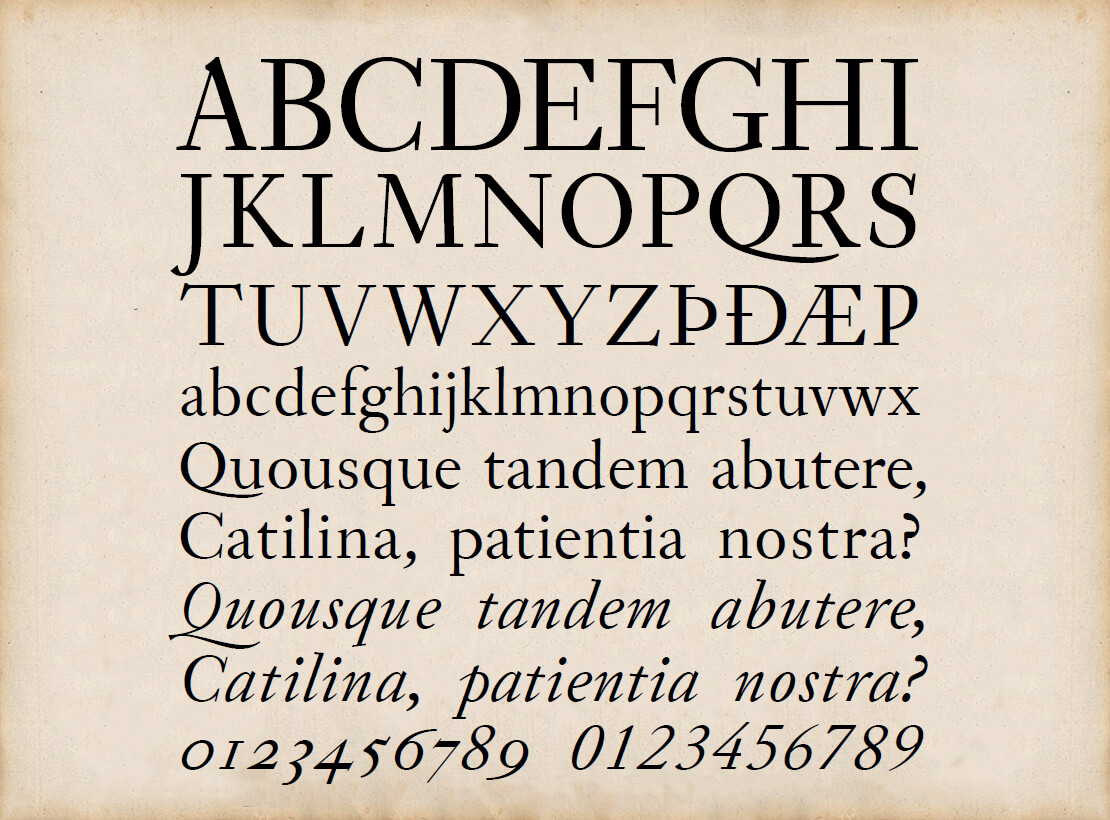
Elstob: Kostenloser Variable Font für Mediävisten und Co.
Ob Altenglisch, Frühneuhochdeutsch oder Altnordisch – Peter Baker vereint in seinem Font-Projekt »Elstob« fast schon vergessene Glyphen mittelalterlicher Sprachen. Entstanden ist eine umfangreich ausgebaute Schriftfamilie, die es kostenlos zum Herunterladen gibt.
Ziel des Font-Projekts ist es, alle gebräuchlichen Unicode-Zeichen, die vor allem für Forschende der mittelalterlichen Geschichten relevant sind, in einer Schrift zu vereinen.
»Elstob« ist benannt nach der Künstlerin Elizabeth Elstob, die im 18. Jahrhundert lebte und als eine frühe Gelehrte der altenglischen Sprache gilt. Die Schrift basiert auf der von Bischof John Fell in Auftrag gegebenen »Double Pica«, die lange Zeit vom Verlag der Universität in Oxford verwendet wurde.
Obwohl sich die Schrift eher an historischen Vorbildern orientiert, weist sie dennoch viele moderne Akzente auf. Darüber hinaus nutzt sie aktuelle Font-Technologie, um eine Vielzahl an OpenType-Features bereitzustellen.
Neben den Variable Fonts gibt es »Elstob« auch in verschiedenen statischen Versionen. Somit kommt die Schrift auf insgesamt 14 reguläre Schnitte – von »Light« bis »ExtraBold«. Zwischenschritte lassen sich außerdem individuell mit den variablen Schriftdateien erstellen, die es auch in einer kursiven Variante gibt.